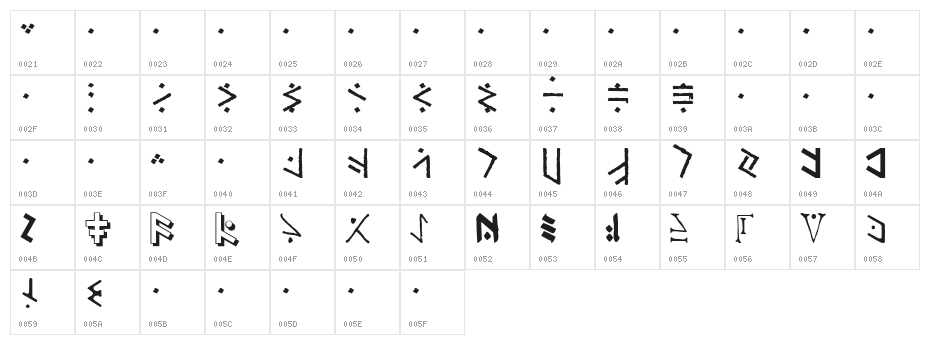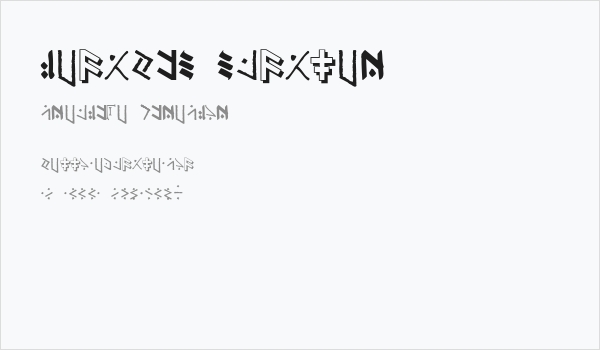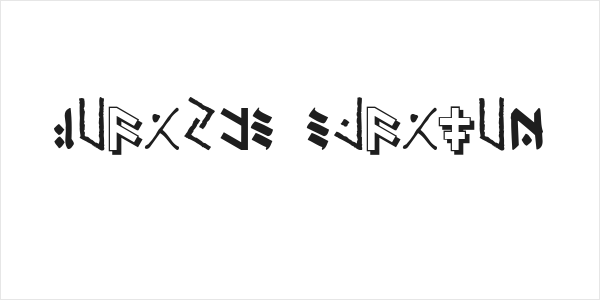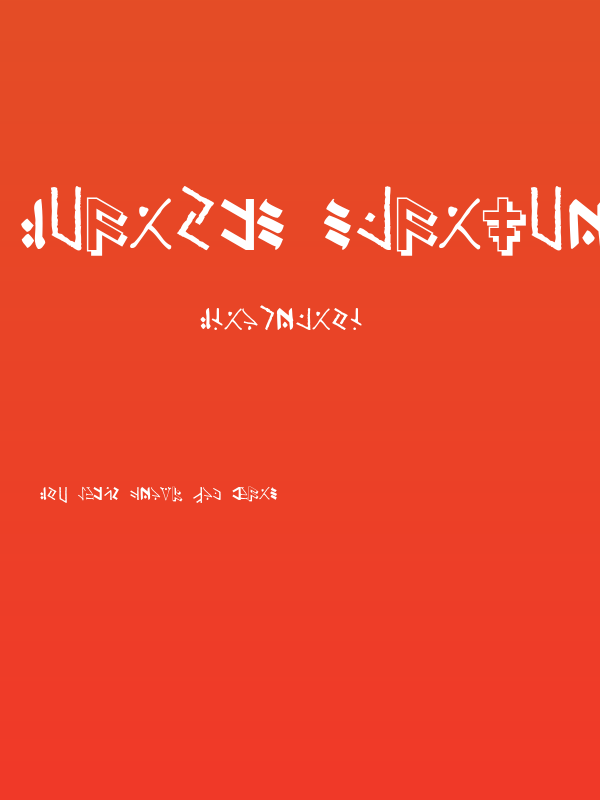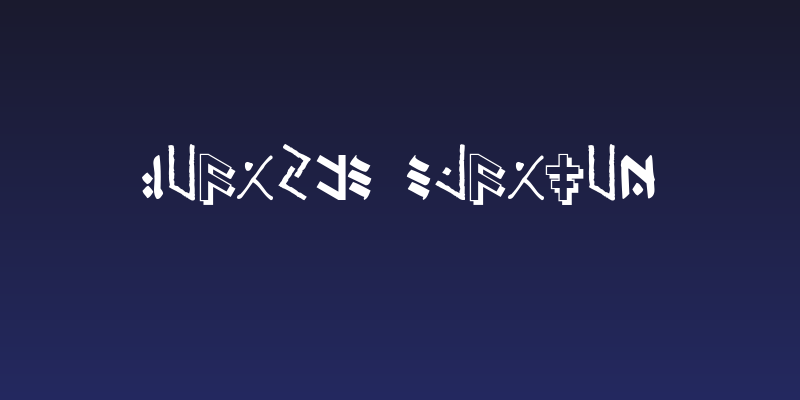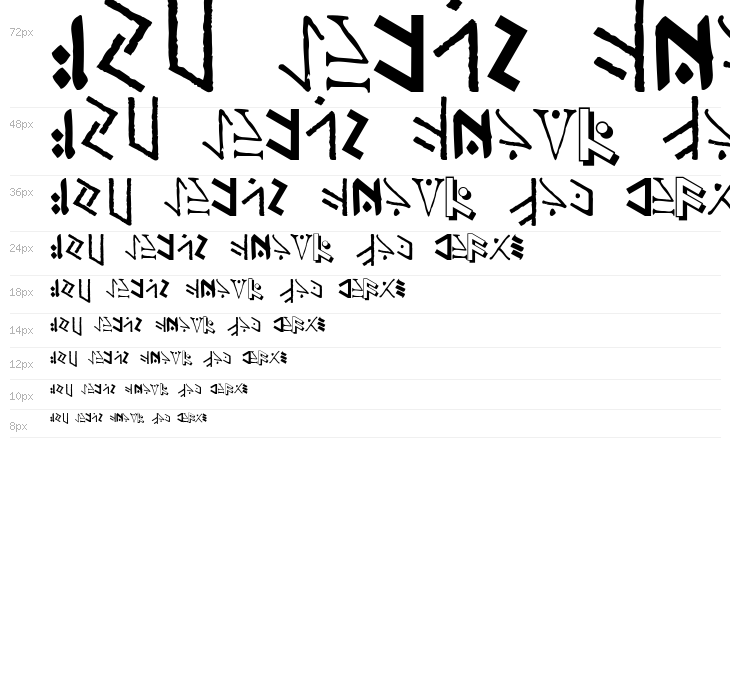
Temphis Sampler Font
| Категория | Quirky |
| Общий стиль | Futuristic, Abstract |
| Область применения | Logos, Titles, Posters |
| Рекомендуемые проекты | Ideal for sci-fi themed projects, video game graphics, movie posters, or any creative work requiring a futuristic and mysterious aesthetic. |